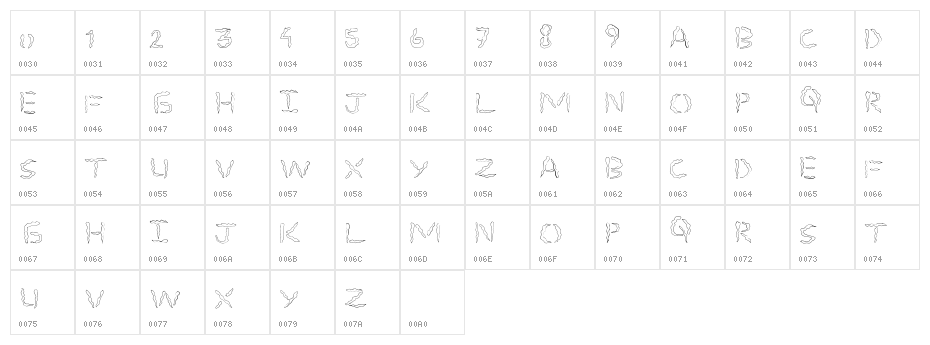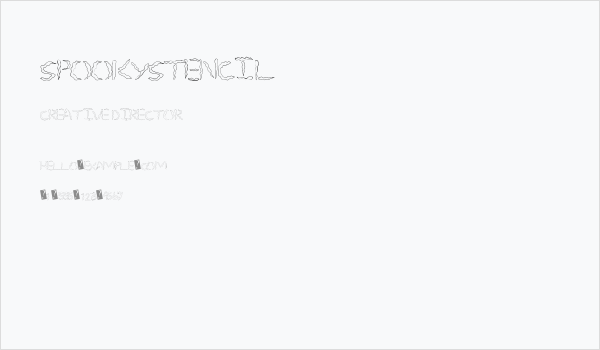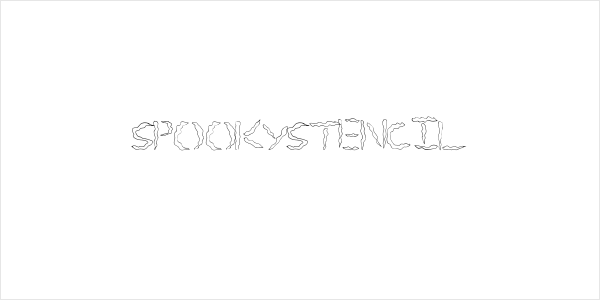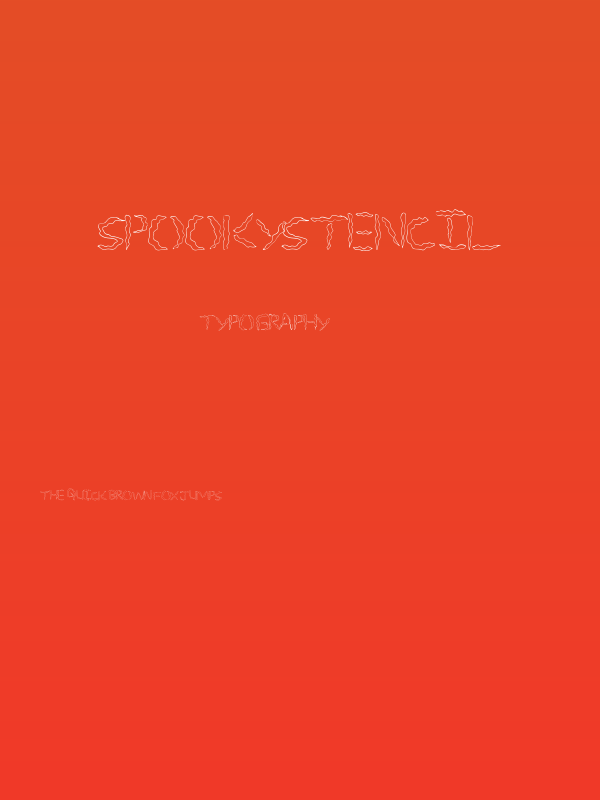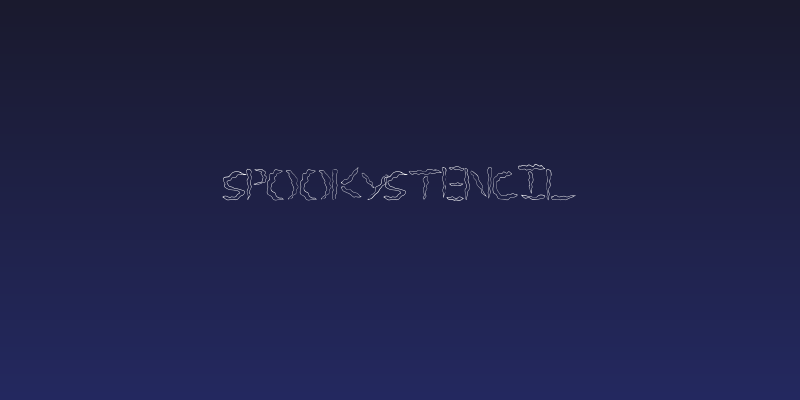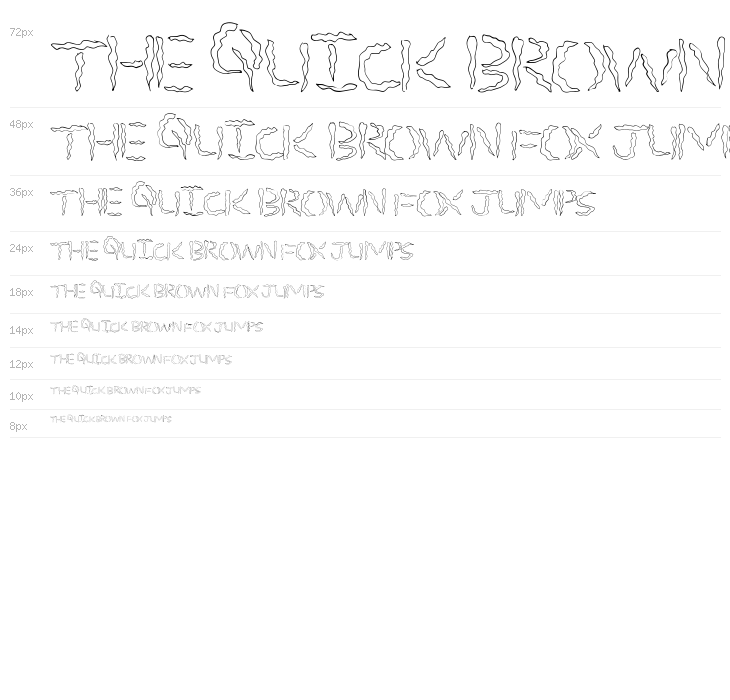
SpookyStencil Font
✎ Stencil
| Vorgeschlagene Projekte | Ideal for Halloween invitations, horror movie posters, themed event flyers, or any project needing a spooky touch. |